Parlons du matériel pour la calligraphie : aujourd’hui, j’ai un petit bureau atelier avec plein de pots, de boites, d’outils, de papiers… Autant le dire, je suis une dingue du matériel : je peux vivre 10 ans avec le même manteau mais je ne résiste pas au plaisir de m’acheter des stylos, des peintures (parce qu’il faut toutes les couleurs, hein, sinon on est frustrés…), du papier de toutes sortes,….pfff… une vraie addiction !
Alors pour être honnête, j’ai du mal à vous dire que pour débuter la calligraphie, il faudra tout simplement :
• Un porte-plume
• Des plumes
• De l’encre
• Des feutres et/ou des pinceaux (pour le brush-lettering)
• Du papier
C’est à la fois vrai – sans ce matériel, pas de calli – et pas vrai parce que ce n’est pas avec ces cinq éléments uniquement que vous allez beaucoup vous éclater. Malgré tout, vous n’allez pas acheter en une fois ce que j’ai mis plusieurs années à accumuler. Ce serait parfaitement déraisonnable et inutile, surtout pour s’initier !
Donc je vous ai concocté une petite liste classée par rayon et par degré d’importance :
Achetez malin !
1. Investissez dans de la qualité pour les couleurs (encre, aquarelle, gouache), les plumes et les pinceaux. En particulier pour les peintures et les encres, fuyez l’entrée de gamme. Vous serez largement récompensés de cet effort.
Pour revenir à nos 5 trésors du calligraphe occidental et moderne, comme ce sont ceux qui posent le plus question, je vous donne plus de précision ci-dessous.
Le porte-plume
Le porte-plume droit bon marché en plastique à levier (Bic), ou en bois font parfaitement l’affaire pour débuter et pour toujours d’ailleurs. Il existe des porte-plume coudés, pour la pratique de l’anglaise, mais ce n’est pas obligatoire pour un débutant.
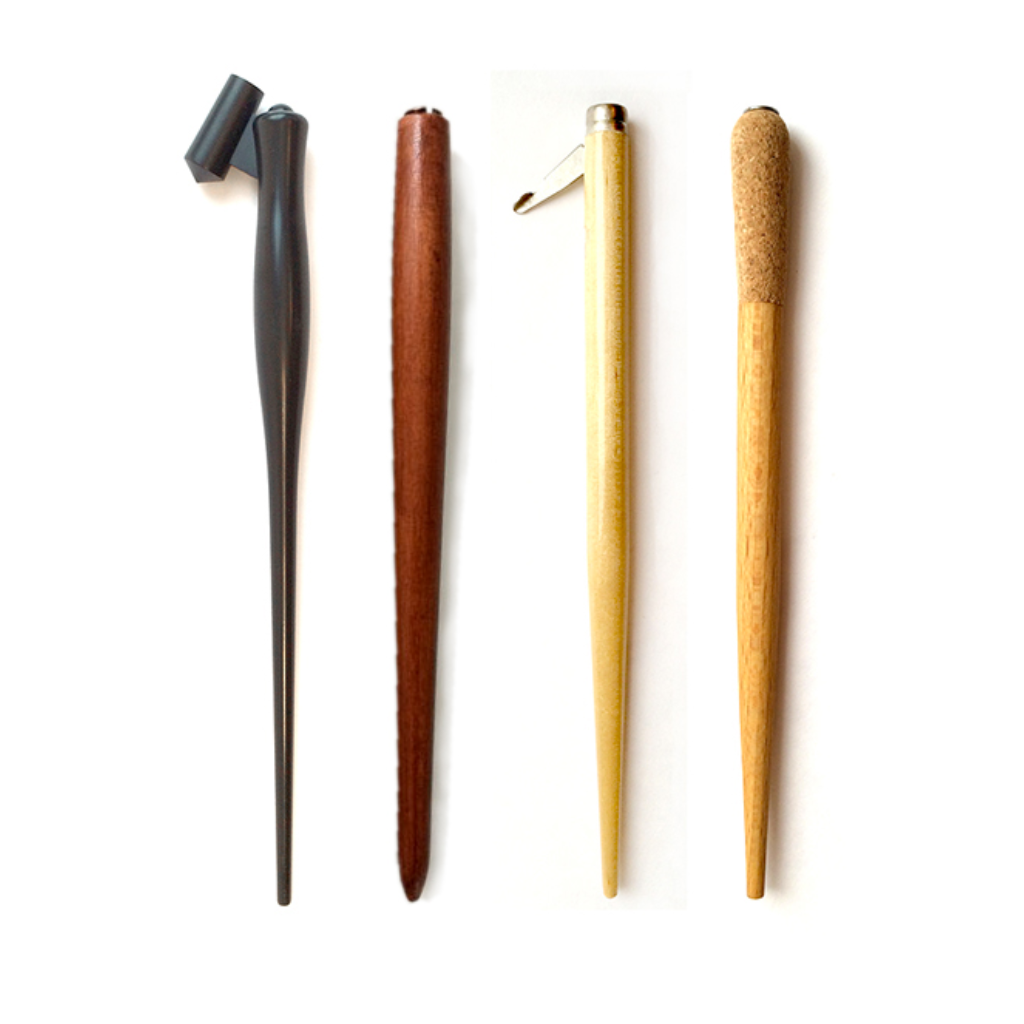
Les plumes
Je vous recommande d’avoir un assortiment avec :
• Des plumes métalliques biseautés Brause Bandzug, de différentes tailles, utiles pour toutes les écritures historiques et plus encore. Robuste, la Bandzug offre une précision inégalée, très appréciable pour les écritures anciennes telles que les gothiques, les onciales, la chancelière, la fondamentale…
Question tailles, prenez l’assortiment de 1 à 3 mm, sachant que vous allez utiliser principalement les grandes tailles (2.5mm et 3 mm) au début.
Notez que la Bandzug existe pour gauchers, avec un biseau adapté (inversé)
Il existe d’autres plumes biseautées (Speedball, Tape), mais pourquoi chercher midi à 14h, s’il ne fallait en acheter qu’une pour débuter ce serait la Brause.
• Des plumes pointues : je consacrerai sans doute un article complet sur les plumes pointues car il en existe de nombreuses sortes, et il vous faudra en essayer plusieurs avant de trouver VOTRE plume, celle qui vous convient et avec laquelle vous aimez écrire. Personnellement, j’ai tendance à beaucoup appuyer sur ma plume, du coup je recherche plutôt des modèles assez… robustes !
Néanmoins, pour débuter, je recommande :
– La Nikko G : précise, contient bien l’encre, à la fois robuste et flexible. Je la trouve idéale pour débuter la Copperplate
– La Gloire de Boulogne de Baignol et Farjon : difficile à trouver malheureusement, mais elle présente les mêmes qualité que la Nikko en plus de produire des déliés beaucoup plus fins et élégants. Elle accroche peu le papier et glisse plutôt très bien. Pour moi c’est THE plume. On la trouve en étant patient, notamment sur ebay où des lots sont parfois proposés à des prix intéressants.
– La Brause Rose : une belle plume de collection, très souple et avec un bon contenant.
Comme indiqué plus haut il en existe beaucoup d’autres, et vous pouvez vous faire un petit assortiment pour les essayer ou les collectionner. Vous trouverez une proposition d’assortiment pour les plumes pointues sur le site de John Neal Booksellers.
| Entretien des plumes : – À la première utilisation, il faut les rincer avec un peu d’eau tiède savonneuse en les brossant délicatement avec une vieille brosse à dent et bien les essuyer pour retirer la pellicule de protection qui est dessus lorsqu’elle sont neuves. On lit parfois de les passer sur une flamme pour faire fondre cette pellicule : tout ce que vous arrivez à faire, c’est à abîmer votre plume, et vu le prix des plumes, vous ne voulez pas cela ! – En entretien courant, il suffit de procéder de même, et de les sécher en dehors du porte-plume afin qu’elles ne rouillent pas, ce qui arrive vite. – Séchez bien aussi votre porte-plume, afin que les parties métalliques ne rouillent pas |
Les encres
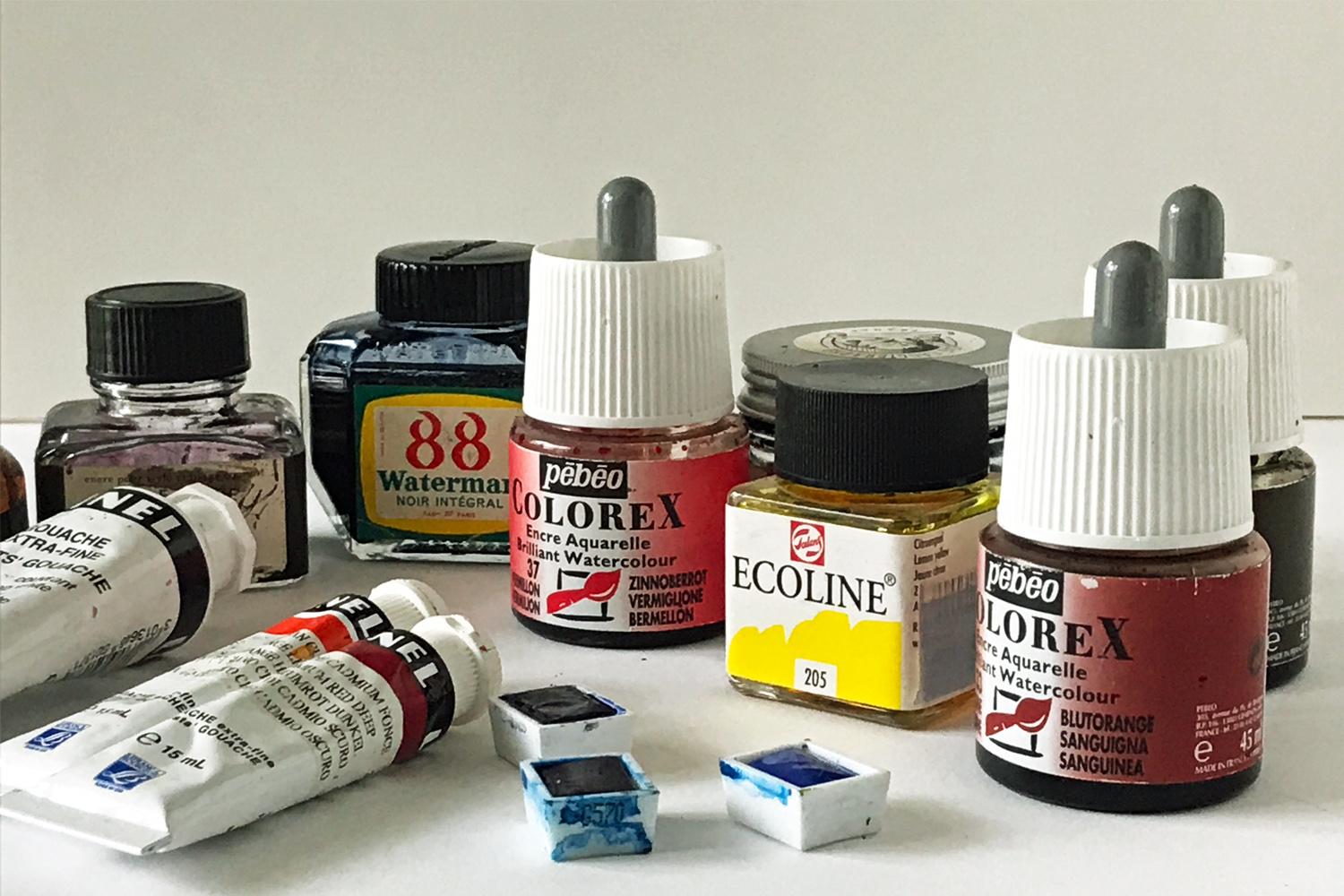
Je ferai un article plus complet sur les encres et les médiums en général, car il y en a de toutes sortes, plus ou moins agréables à utiliser. Pour ma part, j’aime qu’une encre soit fluide, non visqueuse et lumineuse (même pour le noir !). Du coup, j’utilise principalement de l’encre ferrique, de la gouache ou de l’aquarelle diluées.
Les encres pour stylo plume, type Herbin, peuvent aussi être utilisées. Toutefois la couleur n’est pas aussi intense qu’avec les encres aquarelles et c’est plus cher. Mais parfois on a envie de se faire plaisir avec de jolis flacons…
L’aquarelle en godet ou la gouache extra-fine, diluée, fera un excellent médium pour l’écriture. De plus, vous disposerez d’une belle palette de couleurs en un seul achat.
Le brou de noix : acheté dans votre magasin de bricolage, c’est l’encre bon marché par excellence. Le brou de noix est fluide, inodore et agréable à utiliser. On peut le diluer un peu à l’eau. Il faut faire attention, car il tâche les vêtements de façon irrémédiable. Enfin, il n’existe qu’en marron : si vous aimez vous éclater avec la couleur, il faudra prévoir d’autres encres en complément.
L’encre Gallo-Ferrique : c’est l’encre du calligraphe par excellence. Veloutée, précise, profonde, elle résiste aux épreuves du temps. Il existe de nombreuses recettes, mais les ingrédients principaux sont la noix de galle (un parasite du chêne gorgé de tanins) et le sulfate de fer. On peut la fabriquer soi-même, mais en attendant on peut aussi la commander sur le site du Calligraphe.
Précautions à prendre : Il faut soigneusement rincer les plumes, sinon elles rouillent à cause du sulfate de fer. Rincer abondamment et immédiatement les pinceaux, car elle attaque les poils. Enfin, elle tâche irrémédiablement les vêtements. A part ça, on l’adore !
| Attention aux encres dites de » calligraphie » et à l’encre de Chine, que l’on trouve dans les magasins de Loisirs Créatifs: • Souvent visqueuses et collantes, elles encrassent les plumes |
Pour le blanc : les encres blanches (y compris Colorex, Ecoline…) présentent la même viscosité que les encres dites « de Calligraphie ». Elles sont souvent pâteuses, sèchent vite dans le flacon, bref, c’est une galère. La seule encre blanche digne de ce nom est le « Bleed Proof White » Dr Ph. Martin’s. Vous pourrez améliorer la consistance avec quelques gouttes d’eau et une goutte de fiel de bœuf, ou vous replier sur une gouache blanche de très bonne qualité.
On peut utiliser bien d’autres mediums pour écrire, nous le verrons progressivement, l’idée étant ici de fournir les « basiques ».
Des feutres pour le Brush Lettering
Je n’en ai pas testé beaucoup, toutefois j’ai une nette préférence pour le Tombow Dual Brushpen, dont la couleur est dense et la pointe assez nerveuse et précise. Les brushpen aquarelle Windsor & Newton offrent une belle gamme de couleurs, très lumineuses.
Sinon, pour le brushlettering j’utilise tout simplement… des pinceaux !
Du papier
• Un bloc XXL croquis format A3,
• 1 bloc rhodia format A3 à petit carreau ou des copies doubles petit carreaux grand format non perforées. Choisissez une bonne qualité (Clairefontaine, Oxford)
• Tous types de papiers, à grains fins (pour débuter) et qui ne fusent pas…
• Du papier buvard, comme sous-main
Enfin, il vous faudra le petit matériel de bureau de base : crayon de papier, gomme, règle, etc.